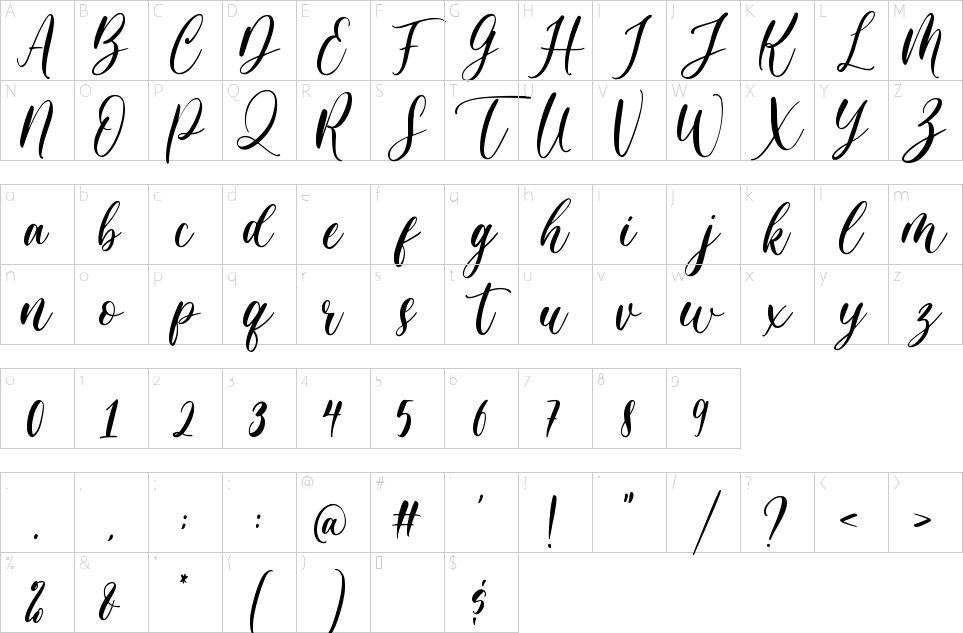
Aqui está uma descrição em português, envolvente e natural, de 2 parágrafos curtos, para uma página de download da fonte ‘Pretty Smile Font | 1001 Free Fonts’: A fonte Pretty Smile é uma opção divertida e descontraída para aqueles que buscam algo leve e alegre em seus projetos digitais. Desenhada com um toque único e repleta de expressões agradáveis, essa fonte é perfeita para adicionar um toque de sorriso em qualquer projeto. Não importa se está criando um site, desenhando uma ilustração ou simplesmente decorando um documento, a Pretty Smile é uma escolha ótima para dar vida a qualquer ideia. Com um design leve e elegante, ela é adaptável para diversos usos, garantindo que seja sempre uma opção versátil e divertida. Se você busca uma fonte leve e alegre, Pretty Smile é uma excelente escolha para adicionar um toque de alegria em seus trabalhos digitais. Com um design minimalista e uma ampla gama de expressões, esta fonte oferece um toque único e divertido a qualquer projeto.